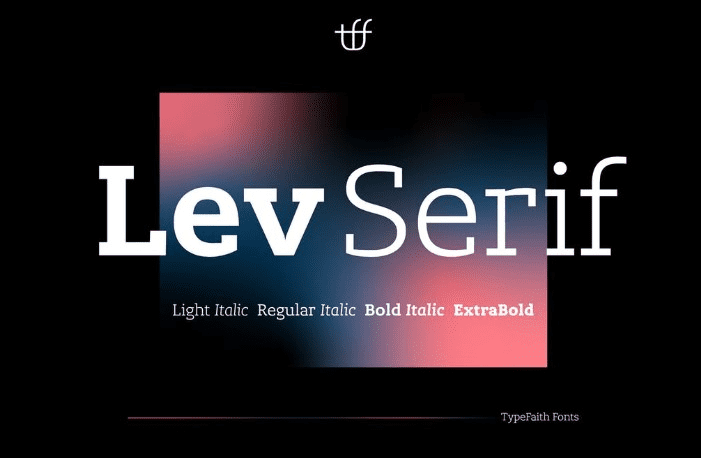
Название: Lev Serif Font
Лев - это плитка шрифта Serif, с прямоугольными засечками с прямыми плечами и изогнутыми связями, контрастирующими с кривыми и петлями.
Для Льва Серифа характерны толстые, блочные засечки.
Лев разработан Леоном Халстом.
Название: Lev Serif Font
Лев - это плитка шрифта Serif, с прямоугольными засечками с прямыми плечами и изогнутыми связями, контрастирующими с кривыми и петлями.
Для Льва Серифа характерны толстые, блочные засечки.
Лев разработан Леоном Халстом.